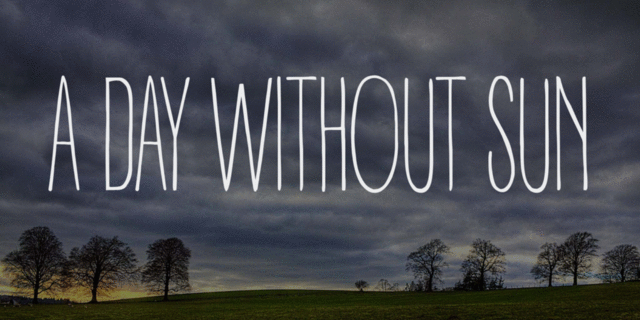
День без солнца – неформальный рукописный хипстерский шрифт, часть шрифтового семейства Pro Panforte. Кроме латиницы, содержит кириллический и греческий наборы символов, а также капитель, лигатуры и минускульные цифры. Шрифт разработан Деборой Манетти в 2014 году и выпущен фирмой Zetafonts. A day without sun by Zetafonts –http://www.zetafonts.com/collection/188
Ассоциации c семейством Day Without SunКачества и характер:
оригинальный, свежий, высокий, стройный, ровный, понятный, лаконичный, современный, модный, живой, доверительный, худой, тонкий, легкий, характерный, воздушный, рукотворный, уютный, приветливый, дружелюбный, приятный, зеленый, природный, интимный, хрупкий, весенний, кустарный, самодельный, семейный, домашний, органический, осенний, грустный, натуральный, вернакулярный